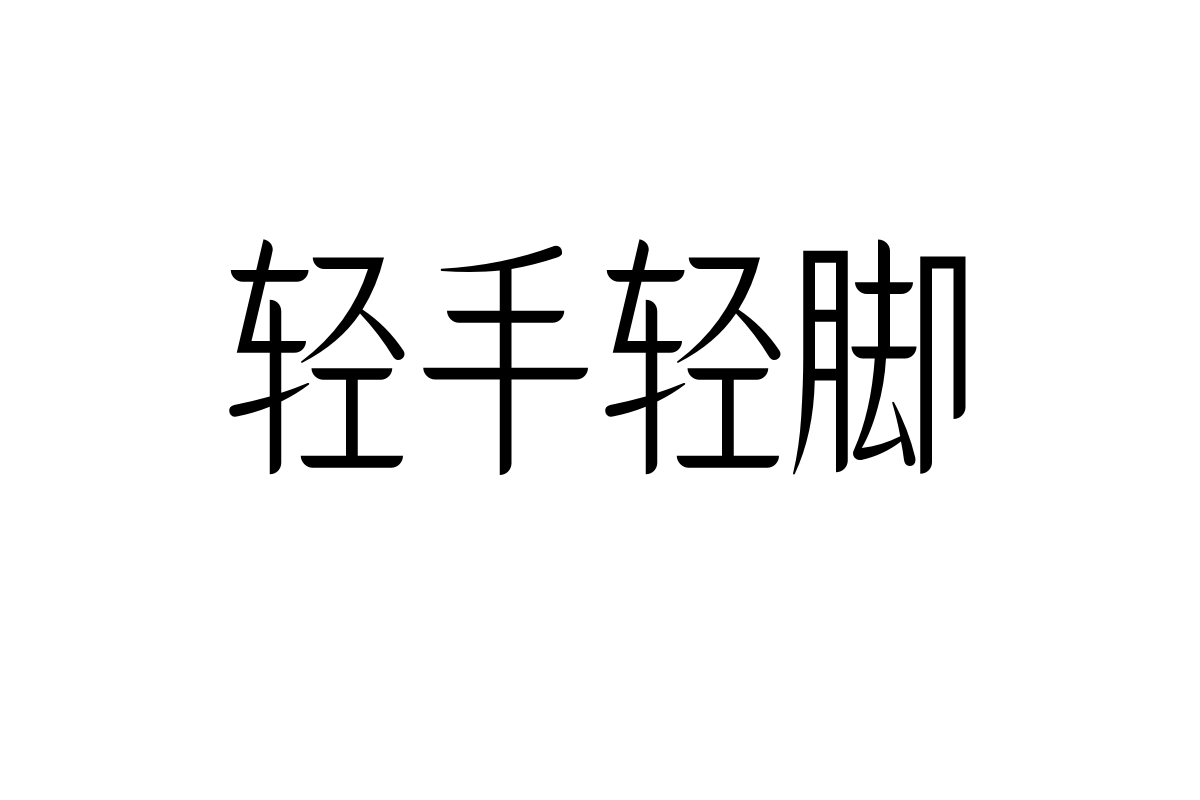
造字工房兰颂体是一款由造字工房公司开发的中文字体,具有独特的艺术风格和现代感。这款字体采用了兰颂体的设计元素,将传统书法与现代设计相结合,创造出了一种全新的字体风格。
兰颂体的特点包括:
1. 字形独特:兰颂体的字形结构独特,线条流畅,给人一种优雅而富有艺术感的感觉。
2. 笔画流畅:兰颂体的笔画流畅自然,没有过多的装饰性笔画,使得整体看起来更加简洁大方。
3. 易于阅读:兰颂体的字形大小适中,间距均匀,使得文字在屏幕上的显示效果清晰易读。
4. 适用范围广泛:兰颂体适用于各种场合,无论是用于网页设计、平面设计还是其他媒体制作,都能展现出其独特的魅力。
总之,造字工房兰颂体是一款具有独特风格和现代感的中文字体,适合用于需要展现个性和艺术感的场合。